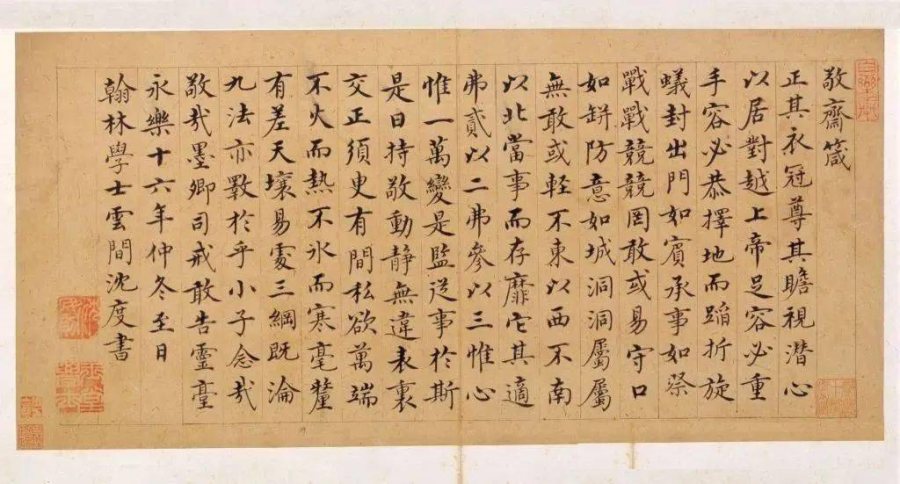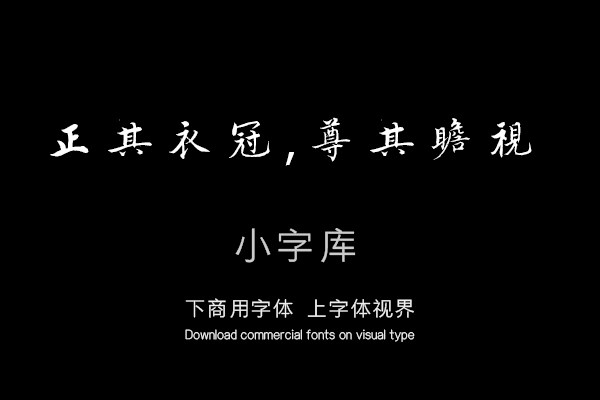
汉标沈度楷书敬斋箴
《汉标沈度楷书敬斋箴》是一款根据明代沈度楷书《敬斋箴》,经过再次调整制作的小字库,该小字库共收录了该真迹作品中约223个字体。
敬斋箴:正其衣冠,尊其瞻视;潜心以居,对越上帝;足容必重,手容必恭;择地而蹈,折旋蚁封;出门如宾,承事如祭;战战竞竞,罔敢或易;守口如瓶,防意如城;洞洞属属,无敢或轻;不东以西,不南以北;当事而存,靡它其适;弗贰以二,弗参以三;惟心惟一,万变是监;从事于斯,是日持敬。动静无违,表里交正;须臾有间,私欲万端;不火而热,不冰而寒;毫厘有差,天壤易处;三纲既沦,九法亦斁;于乎小子,念哉敬哉;墨卿司戒,敢告灵台。永乐十六年仲冬至日。翰林学士云间沈度书